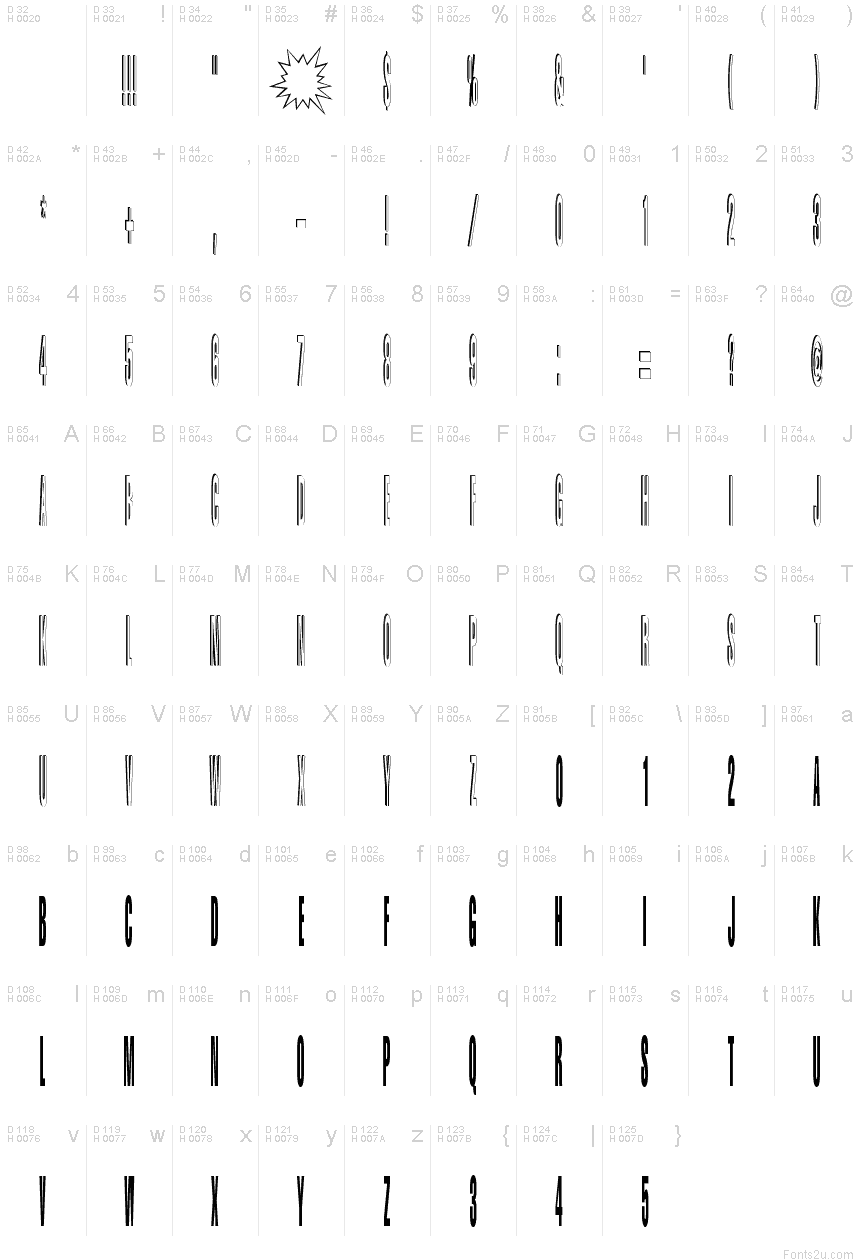
Riesig-Billig od Kai Bergmann je bezplatné úzké titulkové písmo postavené z vysokých, těsně kreslených kapitálek. Těžké vertikální tahy dodávají sazbě plakátovou sílu. Jemné škrábance a nepravidelné otevřené kanálky prořezávají tmavé tvary a dodávají opotřebovanou tiskovou texturu.
Průmyslová hudba a undergroundová kultura jsou přirozeným prostředím pro jeho přísné proporce a poškozený povrch. Hodí se na koncertní plakáty, obaly nahrávek a grafiku streetwearu, kde může zbrázděný vertikální vzor evokovat kopírovanou grafiku, beton nebo zvětralé nápisy.